2000 часов, или КАК СОЗДАЕТСЯ ШРИФТ
От Музея. В ходе Межотраслевого (почти межгалактического) Конгресса «ШРИФТЫ и КНИГИ» Музей побывал этой осенью в гостях у компании «ТайпТайп» (TypeType) — российского разработчика шрифтов.
В их уютном офисе (с изразцовой печью, резными шахматами, креслами-подушками и шоколадными конфетами) на Большом пр. П.С., познакомился с двумя ее симпатичными правителями и не менее симпатичной командой, насладился видами Стены Достижений — с этапами разработки гарнитур, ставших мировыми бестселлерами. И особенно восхитился евро-монетой 2014 года, где используется бесплатный шрифт, созданный со-основателем и техническим директором ТайпТайпа, Иваном Гладких.
Кроме этого Иван Гладких читает лекции в ВШЭ и любезно согласился прочесть для нашей Конференции открытую лекцию о шрифтах, о том, что представляет собой процесс их создания и семи этапах разработки.
Российские компании — разработчики шрифтов
В России существует две шрифтовые компании. Одну из Москвы вы уже знаете, вторая — в Петербурге — мы. [Парайтайп в Москве и ТайпТайп в Санкт-Петербурге. — Прим. ред] В общем и целом мы очень похожи по штату людей, но отличаемся по структуре и принципам работы.
У Паратайпа изначально большая библиотека шрифтов, доставшаяся им исторически. А мы — производственная компания: мы сами придумали все, что рисуем, и хотим делать лучшие шрифты в мире. На сегодняшний день у нас 75+ гарнитур. Каждая гарнитура — это, условно говоря, 18 шрифтов от супер тонкого до жирного, плюс наклонная версия. В шрифте может быть 500 знаков, может быть 1500 знаков — зависит от ситуации, от шрифта, от того, чего мы хотим добиться.
Каждый год мы совершенствуем свои навыки в отдельных направлениях. Чтобы выпускать шрифты часто, много и хорошо, мы разделили процесс их создания на несколько разных этапов.
1 этап. Исследование
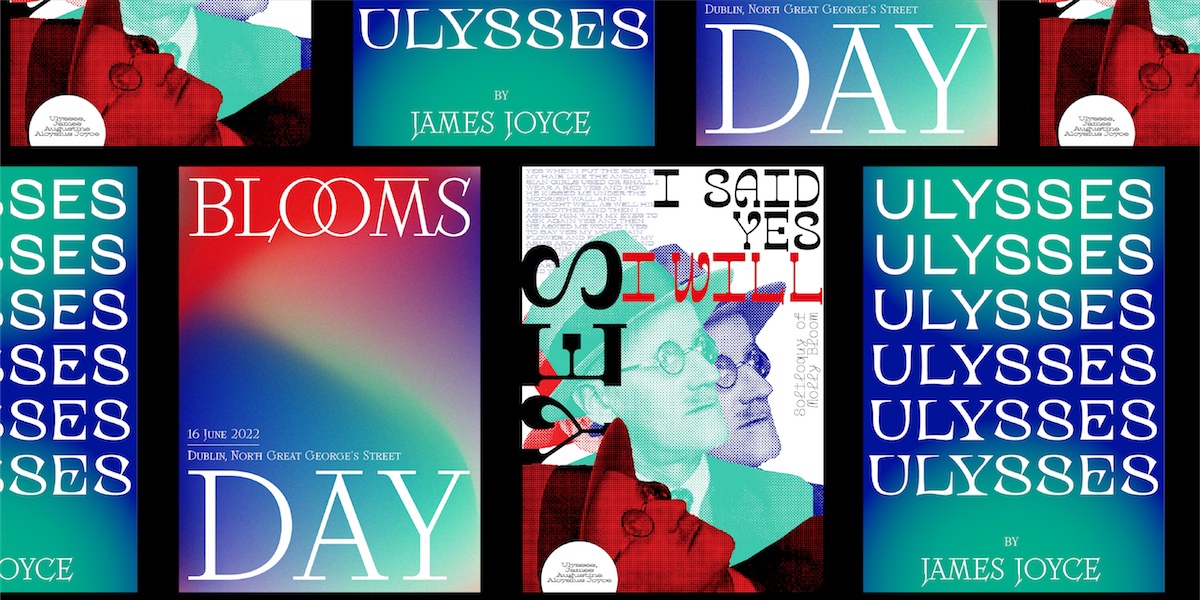
Первый этап — это всегда исследование. Чтобы нарисовать что-то новое, необходимо вложить огромное количество денег. Создание шрифта занимает от 300 человеко-часов до 2000 человеко-часов. Для сравнения: средний год работы без больничных и отпусков — 1700 человеко-часов. То есть фактически мы должны вложить в стоимость шрифта от четырех месяцев до года+ работы одного человека (хотя, понятно, что эти часы разложены на разных людей и реального времени занимает немного меньше). Это очень дорого для проекта, когда не понимаешь, каким будет результат, ведь деньги начнут приходить только после того, как создадим и выложим это.
Поэтому, прежде чем нарисовать что-то большое и затратное по ресурсам, мы делаем маркетинговые исследования по рынку, анализируем, что есть у конкурентов, проводим творческие исследования, смотрим, чего не хватает в кассе у наших шрифтов, что есть у конкурентов и отсутствует у нас.
2 этап. Рисунок основного шрифта
После того как мы получили какое-то внутреннее обоснование, рисуется некий основной шрифт, который будет являться для гарнитуры «титульным». Как правило, это что-то среднее и самое ходовое, типа регулярное медиум начертание, потому что дизайнеры не используют все 18 шрифтов гарнитуры, а покупают какой-то диапазон — регулярное, жирное, наклонное, жирно-наклонное, так называемую «золотую четверку» — Regular, Italic, Bold, Bold Italic.
Как случайно создать мировой бестселлер
У нас есть шрифт TT Commons Pro — это просто гротеск, то есть без засечек. Мы делали его для своих целей и не планировали его продавать, он случайно попал в продажу, и это один из 50-и самых популярных шрифтов в мире, самых продающихся в настоящий момент.
Дело было так: дизайнер разработал для нас фирменный стиль, нарисовал шрифт, мы его собрали, поняли, что он крутой, разместили первые материалы на сайте... А у нас спрашивают: «Где купить?»
«О, "купить"!» — воскликнули мы и доработали гарнитуру. Когда мы ее выпустили, она тут же стала популярной и улетела в ТОП. Кучу лет мы успешно продавали этот шрифт: изначально было 18 начертаний, потом их стало 20, потом — 22, а к настоящему времени их уже 69... В прошлом году полностью его перерисовали: для того чтобы шрифт оставался в ТОПе мы должны его все время обновлять, добавляя либо языки, либо начертания, либо гарнитуру.
3 этап. Процесс отрисовки
Дальше начинается длительный процесс отрисовки, который занимает от нескольких месяцев до полутора лет.
Сначала рисуем основное начертание: уделяется внимание пропорциям, отдельным знакам, каким-то особенностям — арт-директор и старший дизайнер все это подправляют.
Завершив основное, рисуем тонкое начертание — это очень светлое начертание, нарисованное с волосок. Если шрифт с каким-то контрастом, то в нем контраст практически пропадает.
Когда мы смотрим на шрифт, мы воспринимаем его как баланс черного и белого. Регулярное начертание — это что-то среднее между черным и белым. Когда мы смотрим на жирное начертание — это черное на белом. Когда смотрим на светлое начертание — там доминирует белое. То есть это немного разные конструкции с точки зрения именно баланса черного и белого. Соответственно, между этими шрифтами получается интерполяция, чтобы шрифты равномерно прорастали по жирности между собой.
На сегодняшний день студия шрифтового дизайна TypeType — это более 30 сотрудников, 75+ разработанных шрифтов и 800+ шрифтовых начертаний. Шрифты студии используют 35000 клиентов из 110 стран.
В портфолио TypeType не только коммерческие, но и социальные шрифты.
Команда TypeType